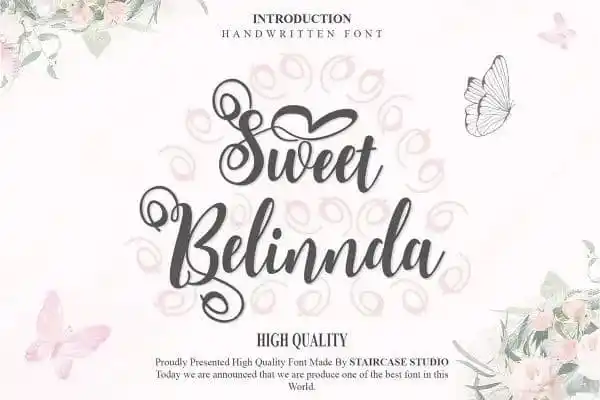
Sweet Belinnda Script Font – Fonte Grátis
Sweet Belinnda Script Font
Descubra a Sweet Belinnda Script Font na categoria de script fonts. Esta fonte foi criada para oferecer uma experiência visual única, com sua mistura perfeita entre handmade calligraphy e ornamentos decorativos. Perfeita para aplicação em cartas de boas-vindas, anúncios, materiais de marcação empresarial, cartões de negócios, cartazes e muito mais. Com sua linha flutuante e estilo elegante, a Sweet Belinnda Script se destaca como uma fonte única para quem busca algo especial em seus projetos gráficos. Testemunhe o encanto da Sweet Belinnda Script em qualquer projeto visual que você desenhe!